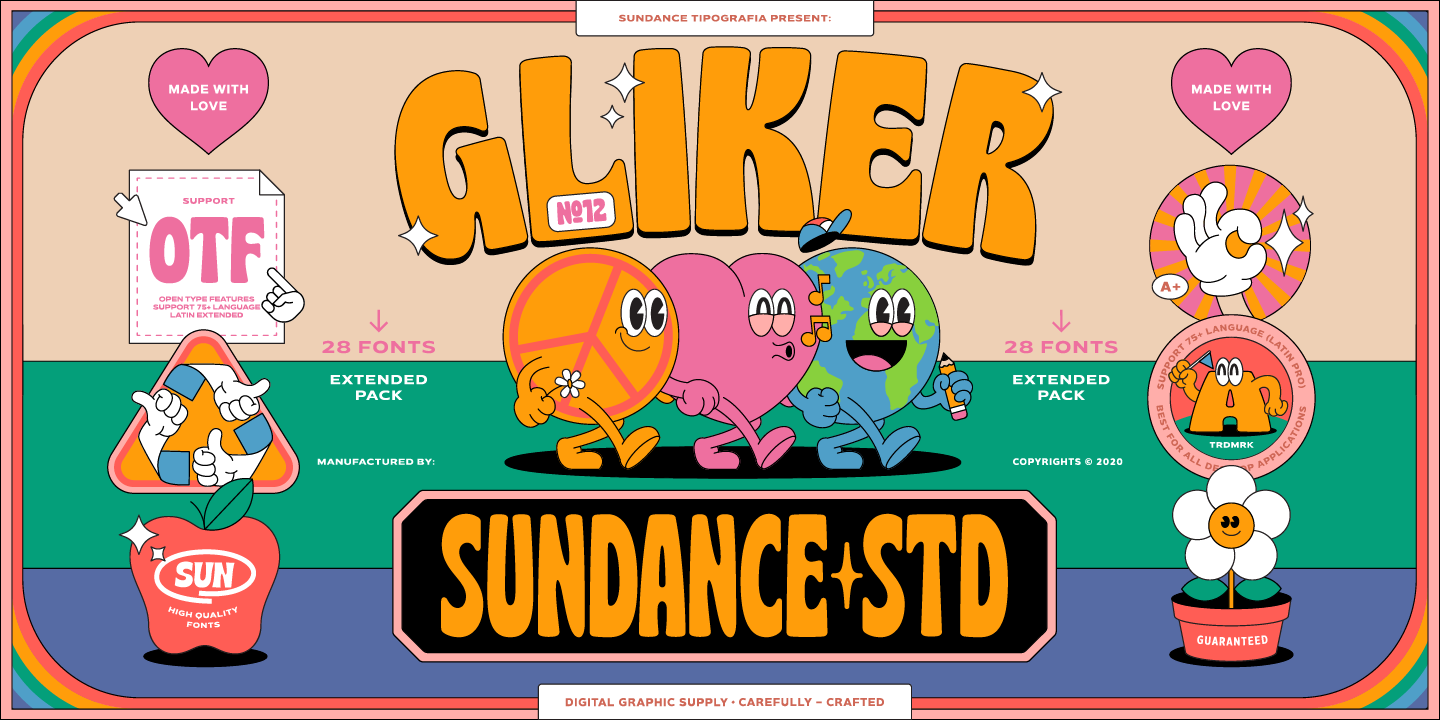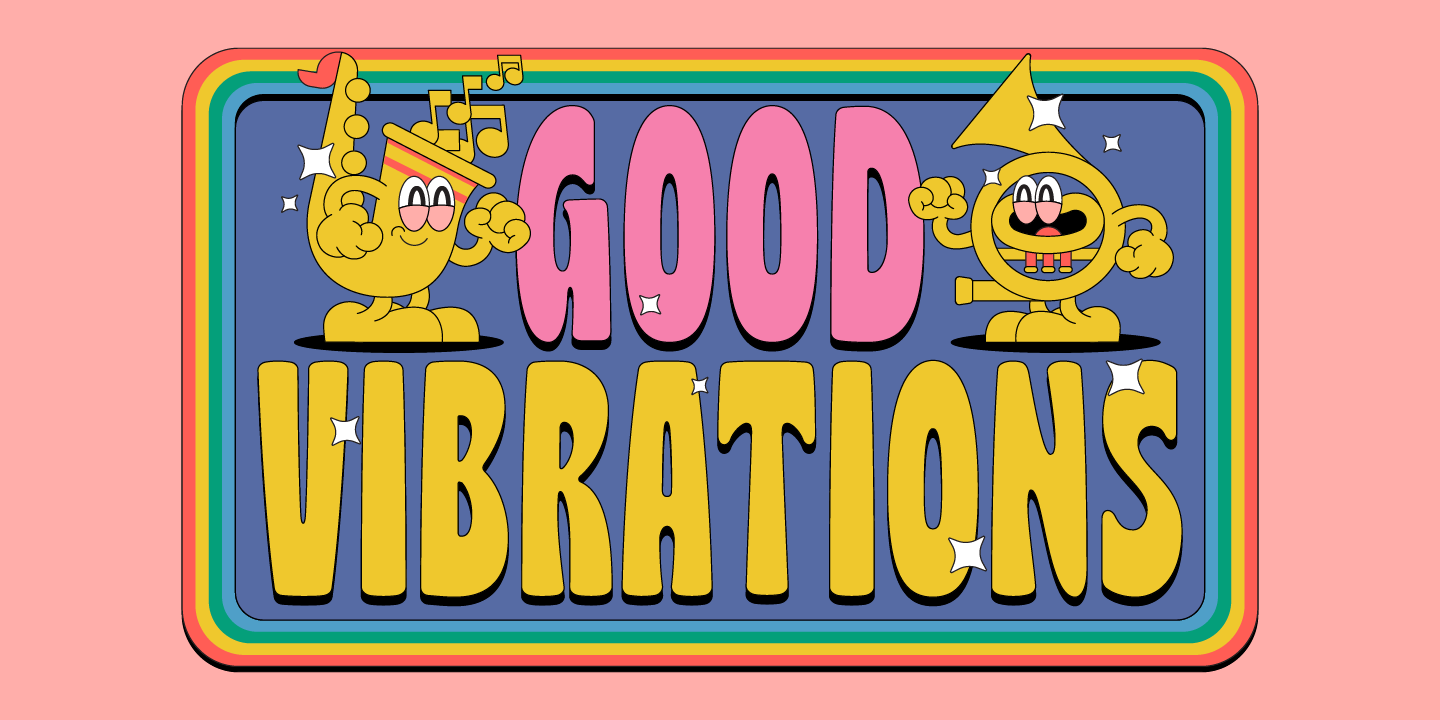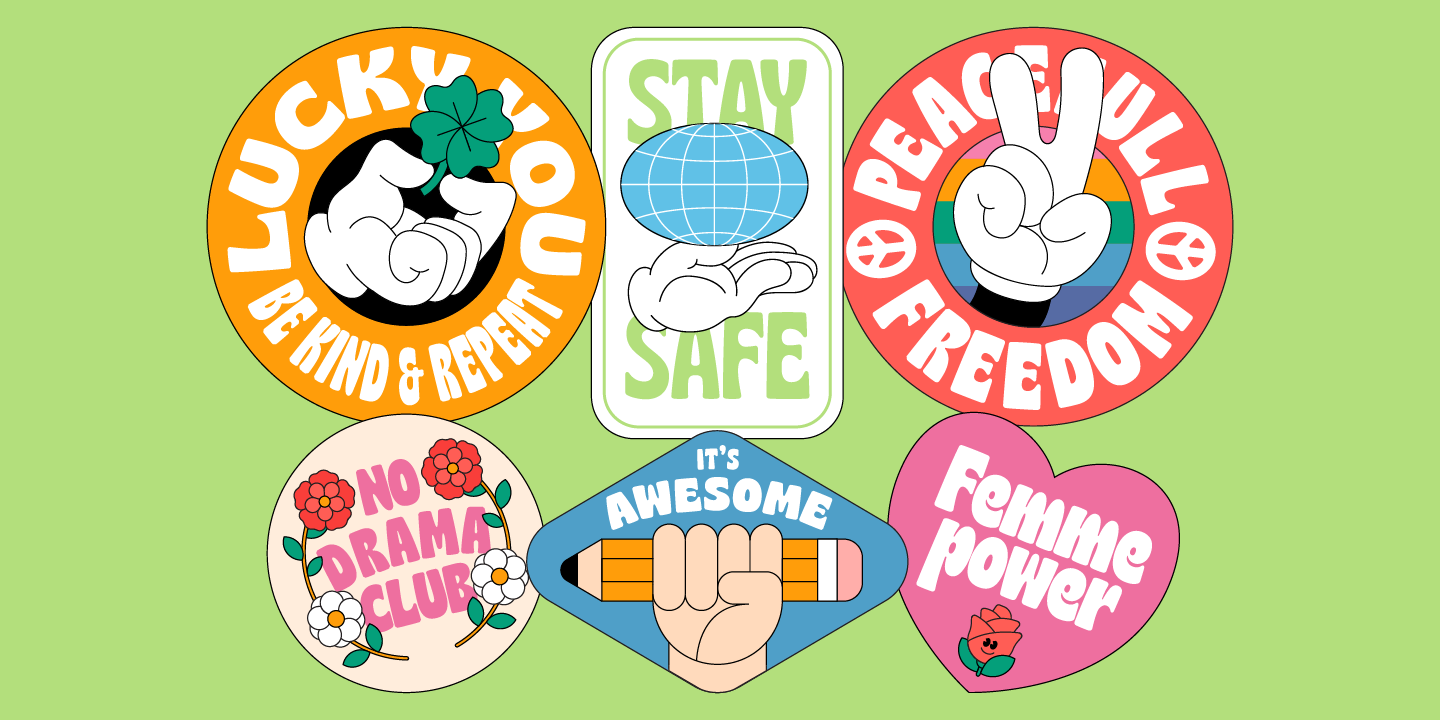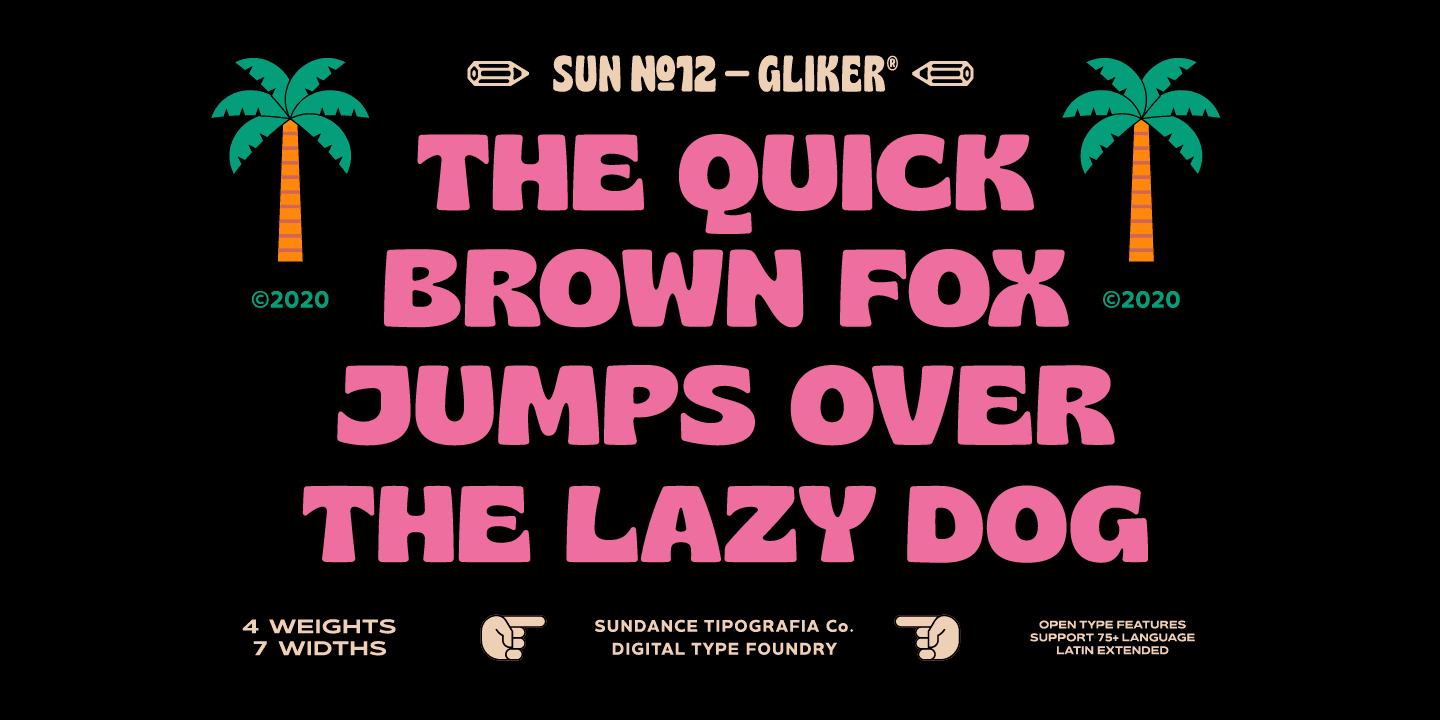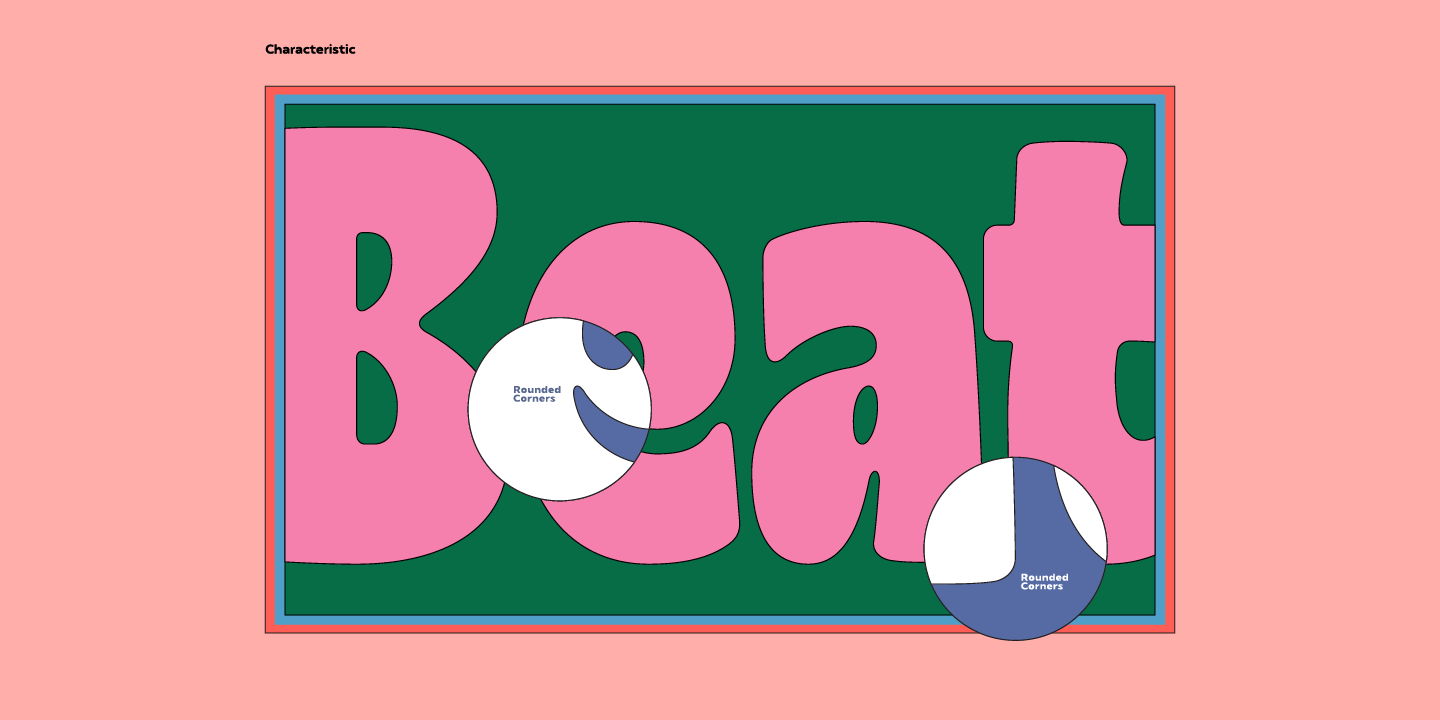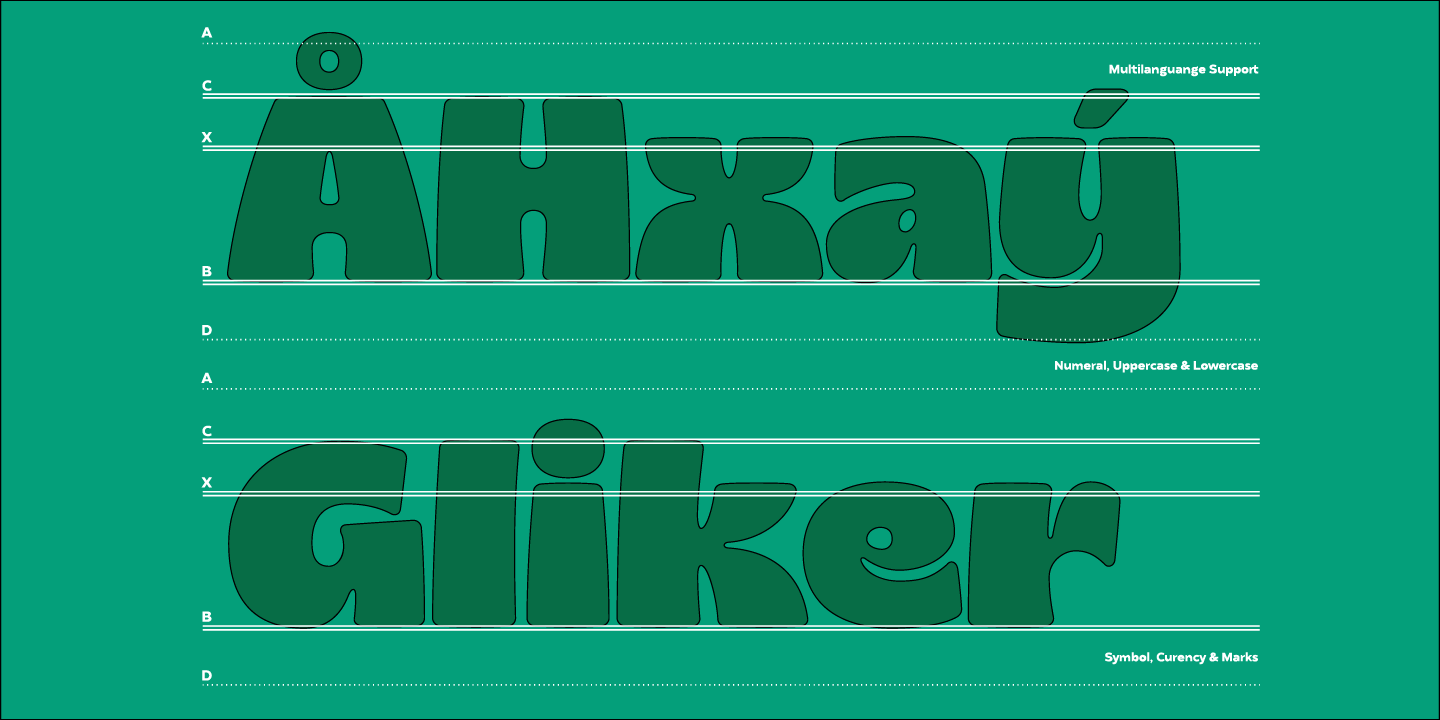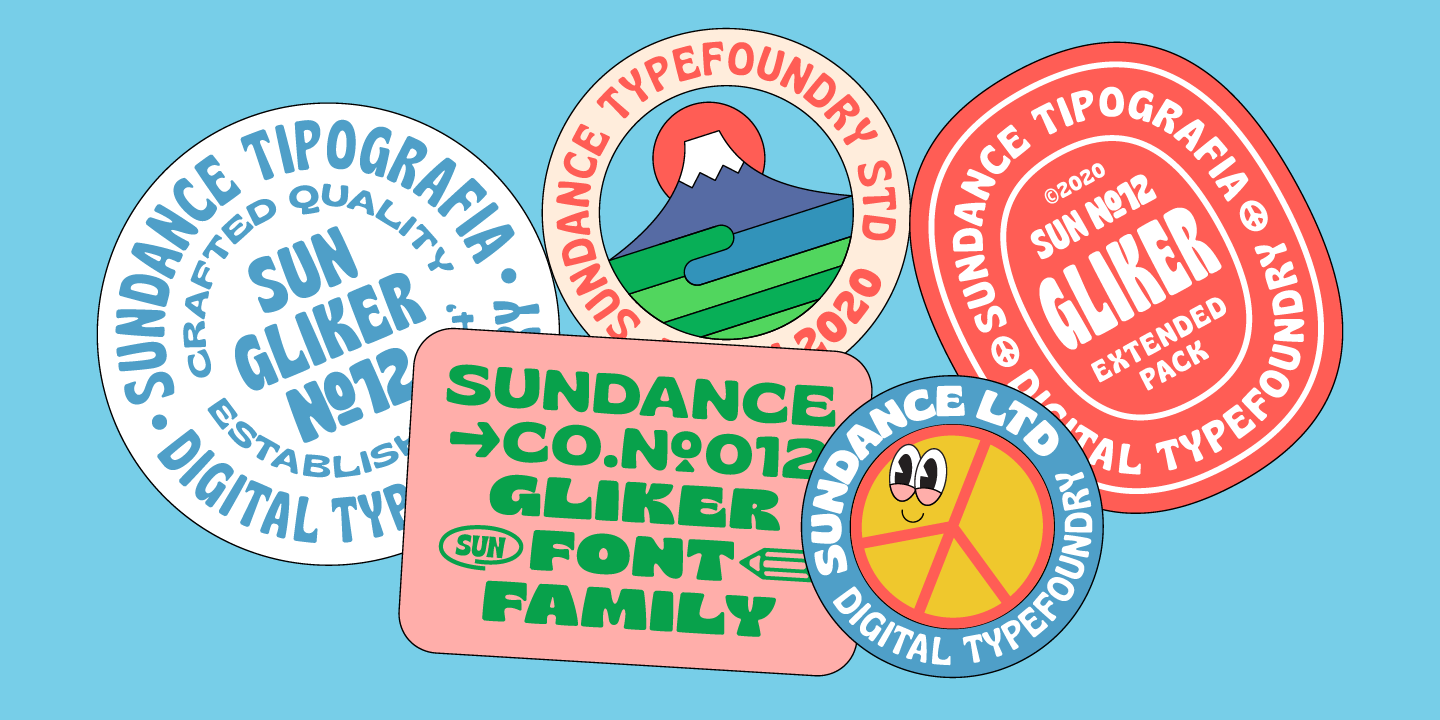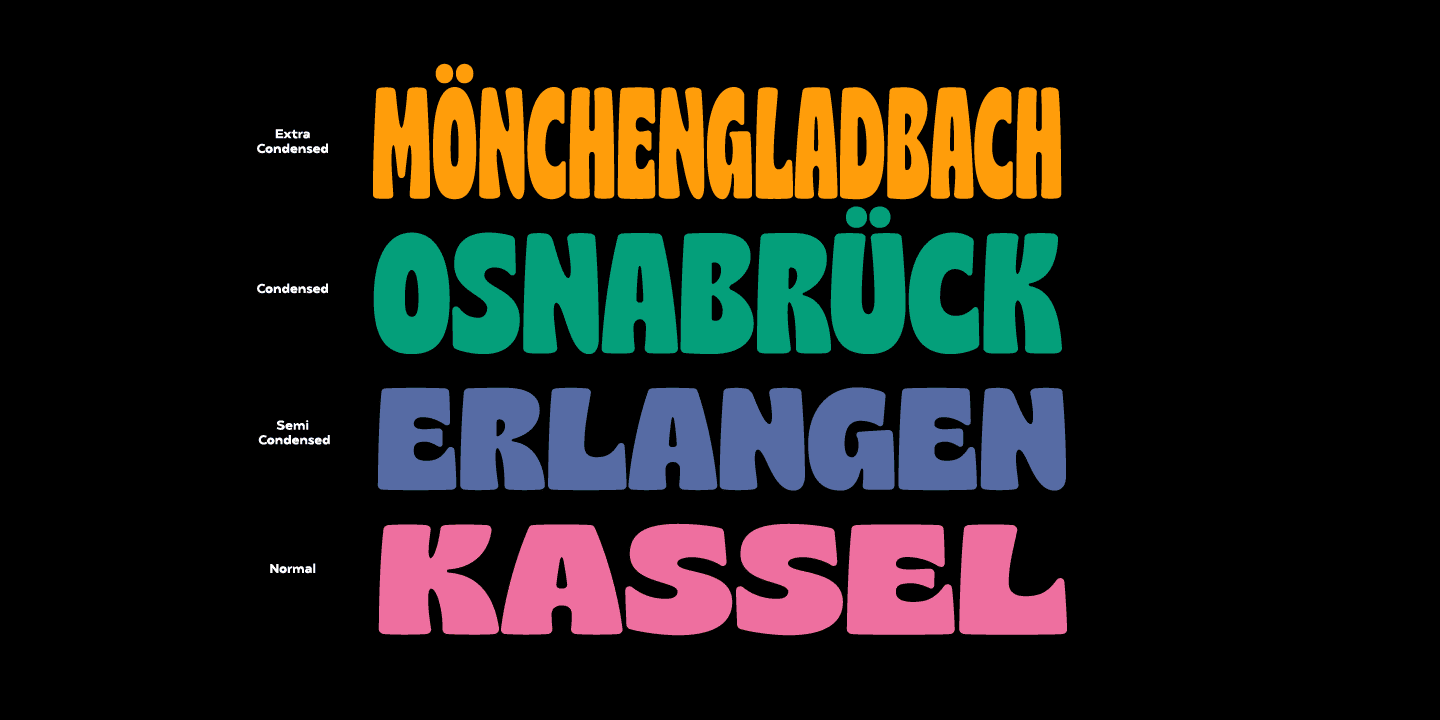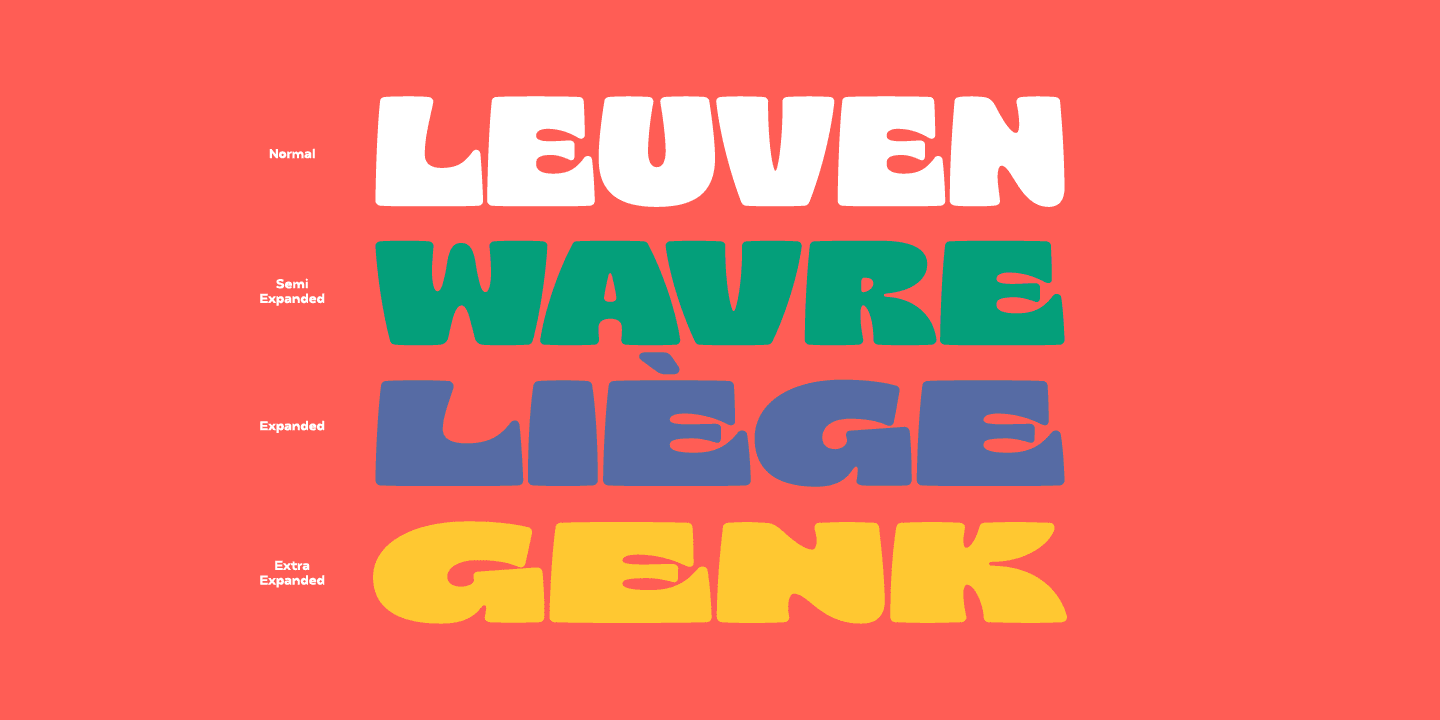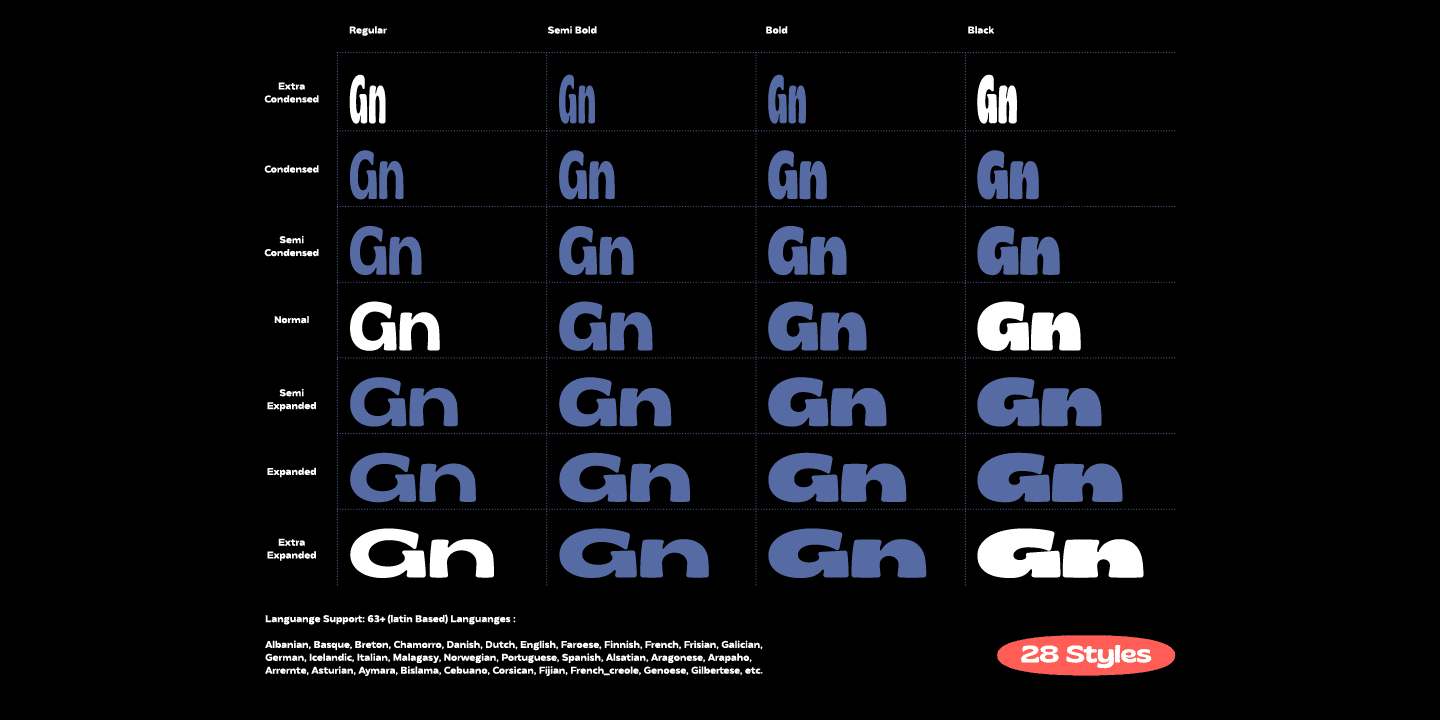
Gliker được thiết kế vào đầu năm 2019 và xuất bản vào tháng 6 năm 2020. Gliker được lấy cảm hứng từ các đặc điểm của Kiểu chữ Hobo. Tất cả các góc của kiểu chữ này đều được thiết kế, mang lại cảm giác năng động và cổ điển hơn.
Gliker có sẵn với 4 Weight (Regular, Semi Bold, Bold, Black) và 7 Width (Extra Condensed, Semi Condensed, Normal, Semi Expanded, Extra Expanded) với tổng số 28 Style. Cũng bao gồm hỗ trợ cho hơn 75 Ngôn ngữ Latinh (Mở rộng).